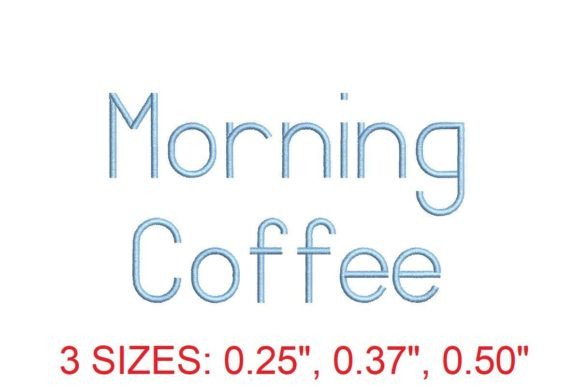
Morning Coffee Embroidery Font
Nếu bạn đang tìm kiếm các tài nguyên chất lượng cao như Morning Coffee Embroidery Font, gói cao cấp này là một lựa chọn tuyệt vời cho các dự án sáng tạo của bạn.
Build Quality & Specifications
Được chế tác với độ chính xác cao, Morning Coffee Embroidery Font cung cấp các vector sạch, kiểu chữ mượt mà và giấy phép thương mại để bạn yên tâm.